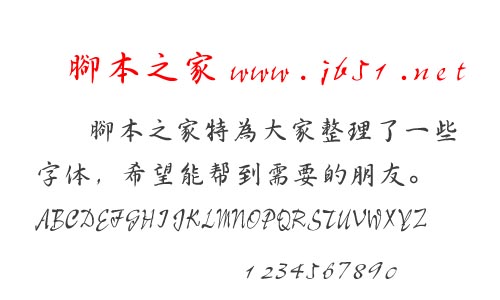
尖端行楷繁體是一款非常不錯(cuò)的行楷字體,風(fēng)格比一般的字體更有特色,連貫字跡顯得干練而不凌亂,清新簡(jiǎn)明,具有很好的視覺(jué)感,適合應(yīng)用于藝術(shù)設(shè)計(jì)、平面宣傳設(shè)計(jì)、網(wǎng)頁(yè)設(shè)計(jì),書(shū)法字帖等領(lǐng)域,歡迎喜歡尖端行楷繁體的朋友前來(lái)下載使用。